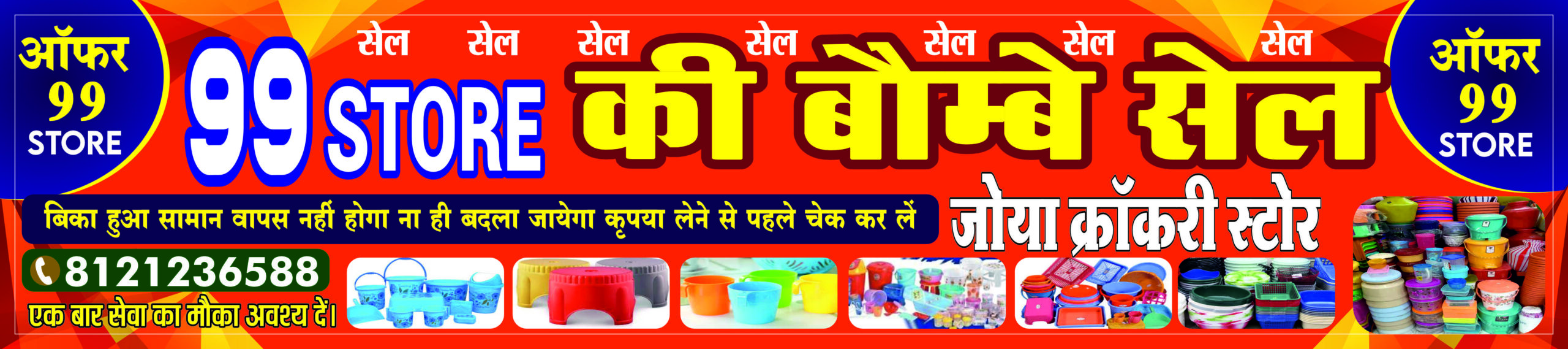
99 Store Sale Banner CDR Design with Font
यह 99 Store (जोया क्रॉकरी स्टोर) का एक अत्यंत आकर्षक और धमाकेदार Sale Flex Banner Design CDR File है। यदि आप एक ग्राफिक डिजाइनर हैं और अपने स्थानीय बाजार के लिए सेल या डिस्काउंट ऑफर का बैनर तैयार करना चाहते हैं, तो यह फाइल आपके काम को रफ्तार देगी। इस डिजाइन को विशेष रूप से “99 स्टोर” और क्रॉकरी आइटम्स की सेल को प्रमोट करने के लिए बनाया गया है।
डिजाइन में लाल और चमकीले पीले (Sunburst) बैकग्राउंड का उपयोग किया गया है, जो किसी भी सेल या ऑफर के लिए सबसे प्रभावी माना जाता है क्योंकि यह दूर से ही लोगों की नजरों को अपनी ओर खींचता है। बैनर में बाल्टी, मग, स्टूल, टब और किचन के अन्य प्लास्टिक और क्रॉकरी सामानों की वास्तविक फोटो का इस्तेमाल किया गया है, जिससे ग्राहकों को तुरंत समझ आ जाता है कि दुकान में क्या उपलब्ध है। “99 Store की बॉम्बे सेल” जैसे बड़े और बोल्ड फोंट्स ग्राहकों के मन में कौतूहल पैदा करते हैं।
यह डिजाइन पूरी तरह से कस्टमाइजेबल है। आप इसमें अपनी दुकान का नाम, नया मोबाइल नंबर और सेल की शर्तें आसानी से बदल सकते हैं। इसकी बनावट ऐसी है कि यह बड़े फ्लेक्स बोर्ड से लेकर छोटे पोस्टर तक हर साइज में प्रिंट होने पर बेहतरीन क्वालिटी देता है।
Product Highlights (मुख्य बिंदु)
• Eye-Catching Color Scheme: सेल के लिए परफेक्ट रेड और येलो वाइब्रेंट कलर का चुनाव किया गया है।
• Ready-to-Use Images: इसमें उच्च गुणवत्ता वाले प्लास्टिक और क्रॉकरी आइटम्स की इमेजेस पहले से ही सेट हैं।
• Clear Call-to-Action: मोबाइल नंबर और “ऑफर 99 स्टोर” को अलग से हाईलाइट किया गया है ताकि संपर्क करना आसान हो।
• Editable Disclaimer: “बिका हुआ सामान वापस नहीं होगा” जैसे महत्वपूर्ण दिशा-निर्देशों को स्पष्ट रूप से शामिल किया गया है।
• Versatile Layout: इस डिजाइन को आप किसी भी सेल इवेंट, मेला या फेस्टिवल डिस्काउंट के लिए इस्तेमाल कर सकते हैं।
• Premium Hindi Fonts: डिजाइन में इस्तेमाल किए गए हिंदी फोंट्स बहुत ही बोल्ड और स्टाइलिश हैं जो इसे एक प्रोफेशनल लुक देते हैं।